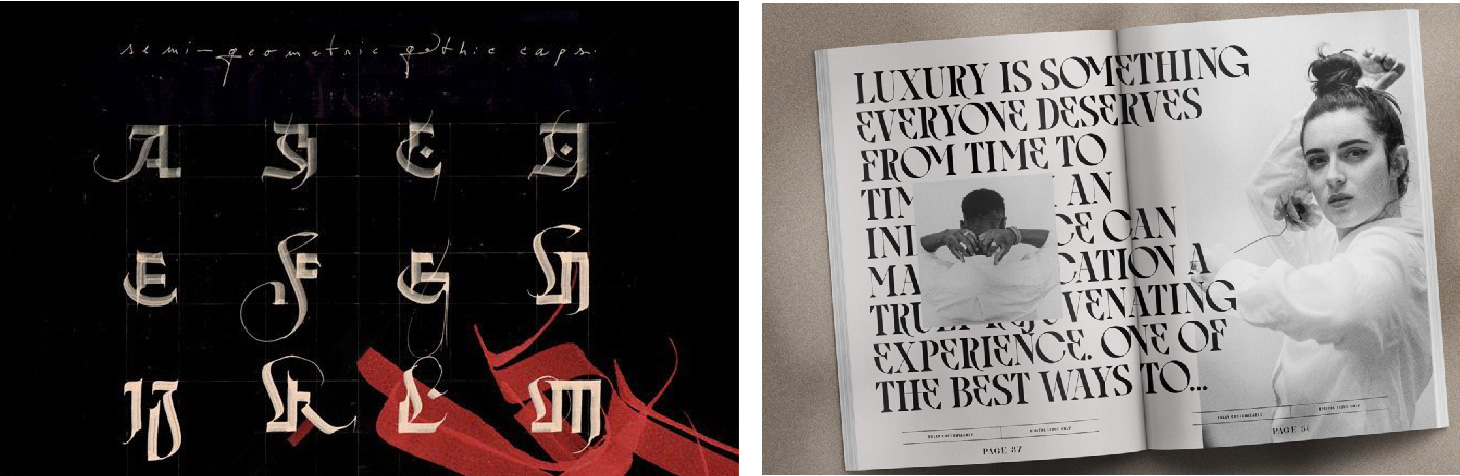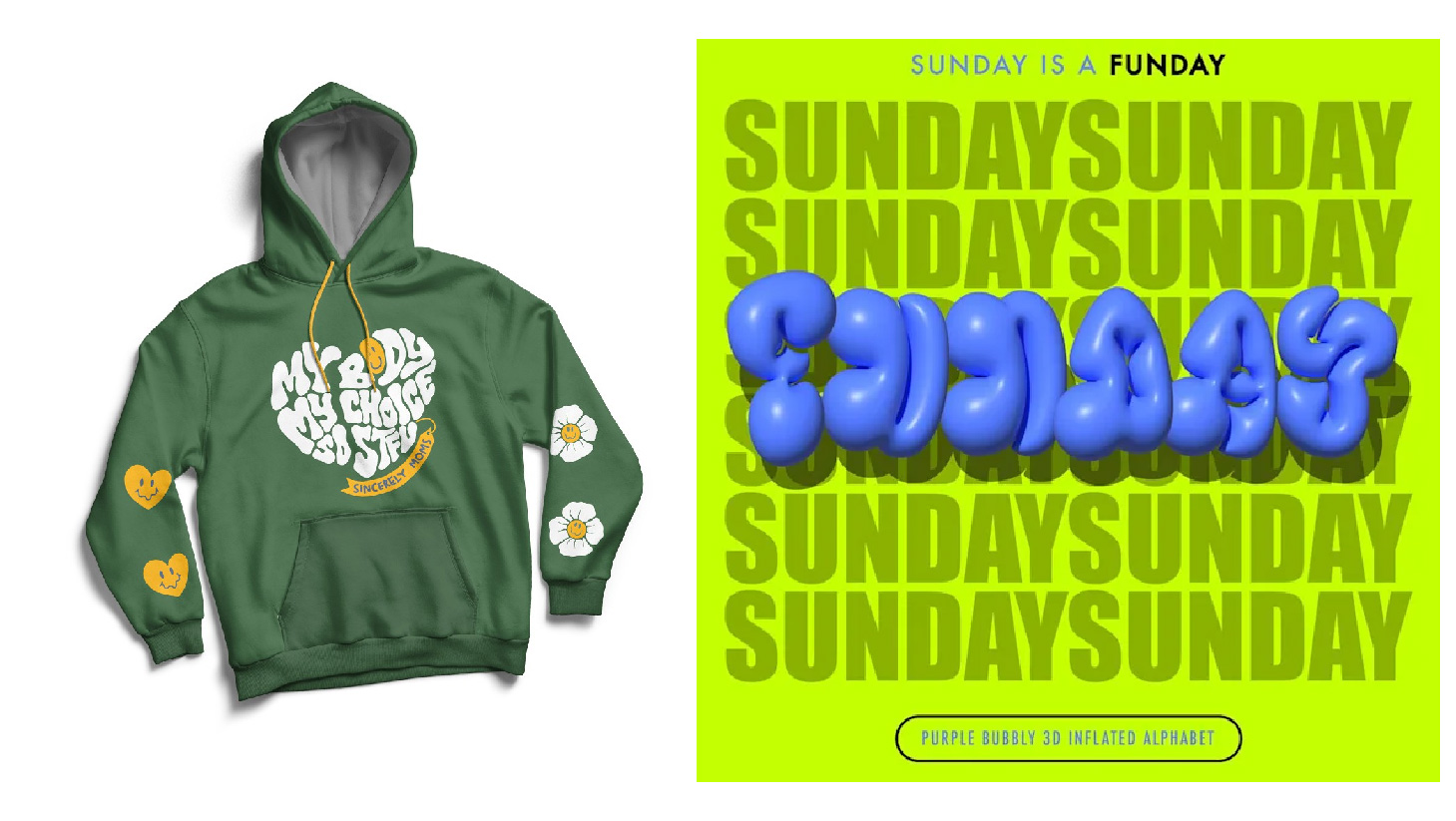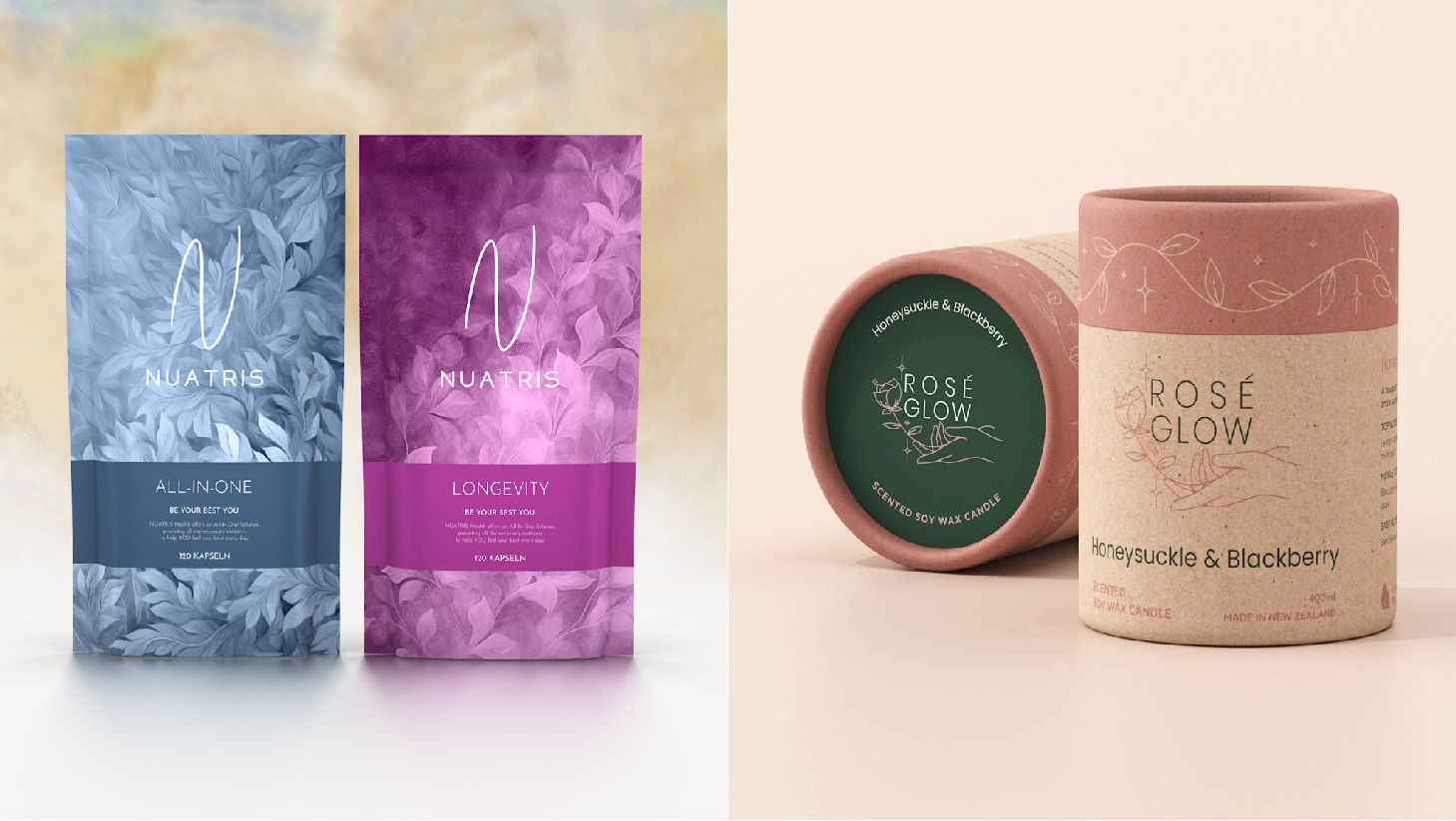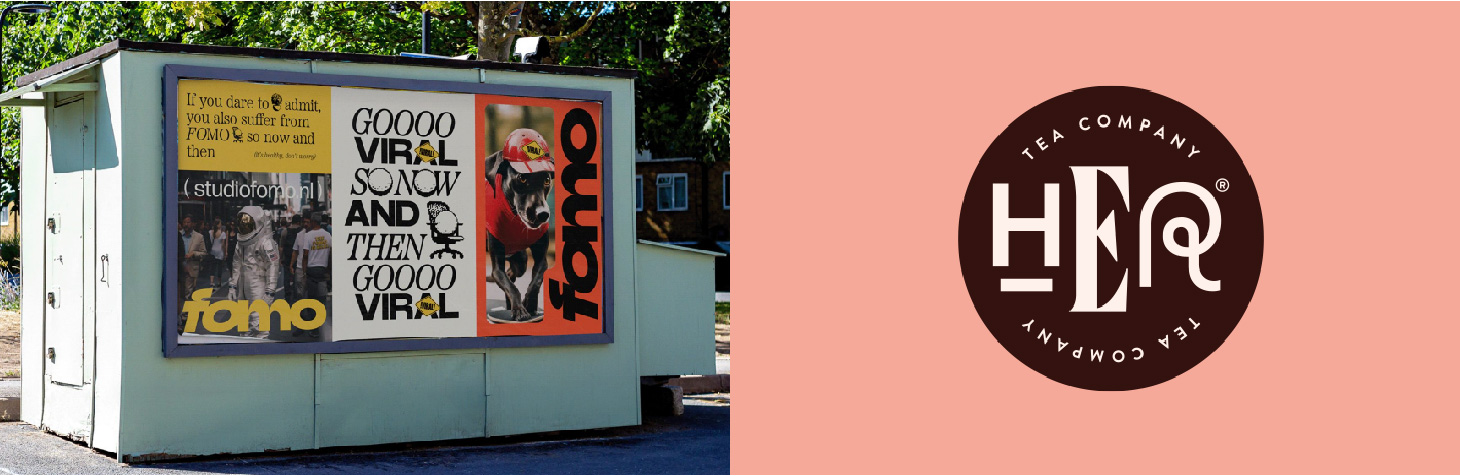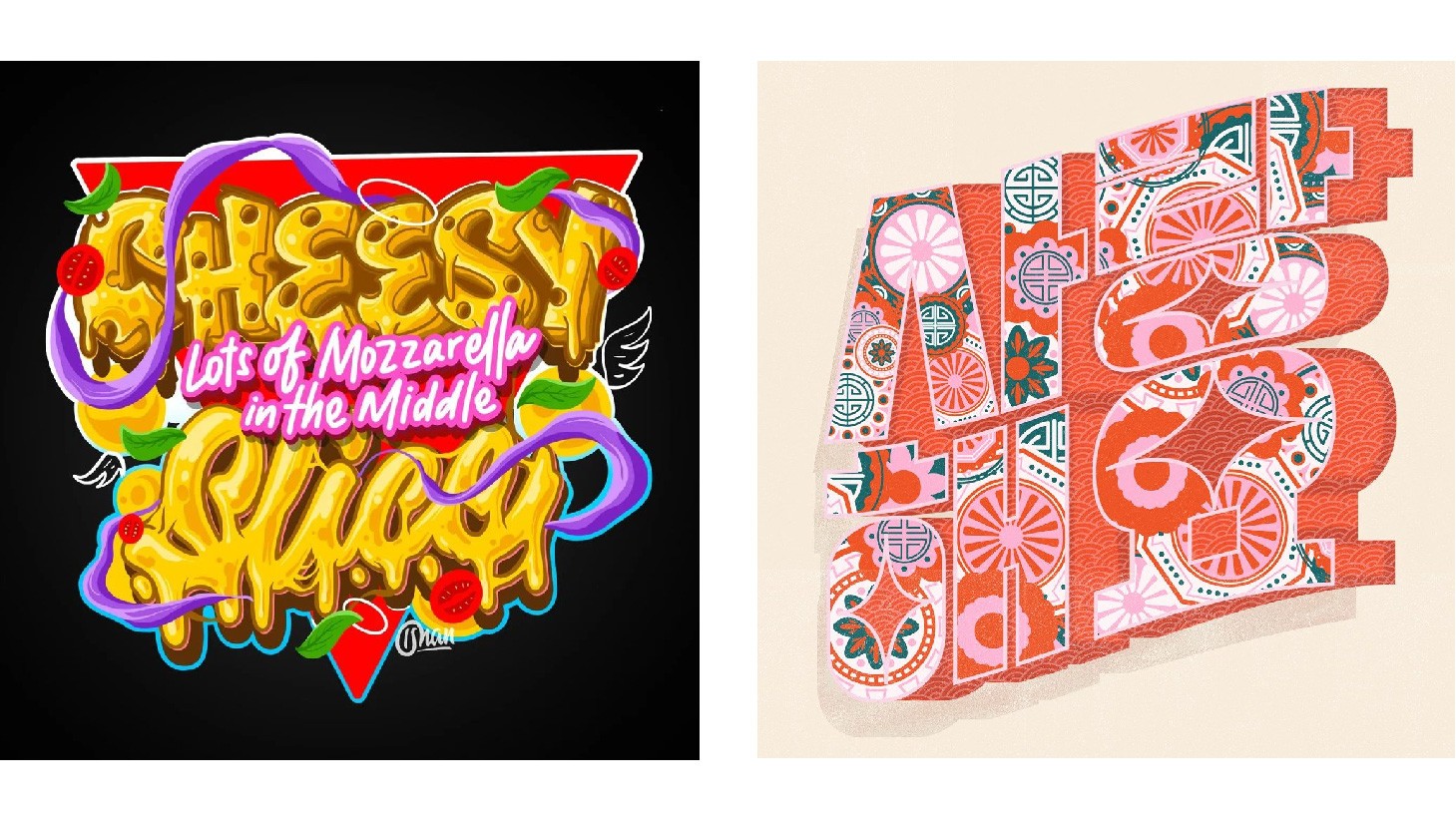
5 xu hướng thiết kế font chữ năm 2026 mà bạn không thể bỏ qua
Cùng Bee Art khám phá 5 xu hướng thiết kế font chữ 2026 được dự đoán sẽ làm mưa làm gió nhé!
Sự thay đổi của font chữ trong năm 2026
Nghệ thuật thiết kế đồ họa đang thay đổi với tốc độ chóng mặt. Mỗi năm, những công cụ mới và xu hướng thẩm mỹ mới lại định hình cách chúng ta đọc và cảm nhận thiết kế. Và 2026 là một năm đầy hứa hẹn với nhiều chuyển biến đột phá. Font chữ giờ đang trở thành “nhân vật” thật sự trong thế giới thiết kế: Yếu tố tạo nên cảm xúc, nhịp điệu và cá tính cho thiết kế. Từ typography chuyển động, 3D, đến màu sắc sinh động và kiểu chữ thủ công, năm nay là thời điểm mà font chữ trở nên sống động, linh hoạt và đầy sức biểu cảm.
Sự trở lại của font chữ hoài cổ - Retro
Năm 2026 là thời điểm cảm hứng hoài niệm gặp gỡ nét cá tính hiện đại. Các font chữ mang phong cách retro đang trở lại mạnh mẽ: Từ slab serif đậm nét, đường cong phóng khoáng của thập niên 70, đến chữ viết tay cổ điển vui tươi nhưng được làm mới trong bố cục mới đầy phá cách. Khi được kết hợp với chất liệu thô, bề mặt sần hay đường nét chữ phóng khoáng, không đều đặn, phong cách này mang lại cảm giác tự nhiên, chân thật và tràn đầy sức sống.
Xu hướng Font chữ cách điệu hoài cổ đang trở lại
Những font chữ retro đặc biệt phù hợp với thiết kế thương hiệu, poster hoặc ấn phẩm biên tập, nơi cá tính thị giác được đặt ngang hàng với khả năng đọc dễ dàng.
Font chữ thủ công, chữ viết tay (Handcrafted Fonts)
Giữa thời đại mà mọi chi tiết đều được căn chỉnh hoàn hảo đến từng pixel và AI có thể tạo ra font chữ chỉ trong chớp mắt, những nét chữ mang dấu ấn lại trở nên thật đặc biệt.
Font chữ viết thủ công thường có đường nét không đều, nét cọ phóng khoáng, bề mặt gồ ghề hay chút lem mực tự nhiên – chính những “khuyết điểm” ấy lại làm nên cá tính và cảm xúc riêng. Chúng mang lại sự ấm áp, gần gũi và chân thật, khiến người xem có cảm giác như đang chạm vào nét chữ thật được vẽ bằng tay.
Ngày nay, bạn có thể bắt gặp font chữ thủ công trong thiết kế thương hiệu, bao bì sản phẩm, bìa sách hay ứng dụng di động - ở bất cứ đâu mà thương hiệu muốn gần gũi, thân thiện.
Font chữ viết tay thủ công sẽ làm mưa làm gió năm 2026
Giữa thế giới của những thiết kế “chuẩn chỉnh” và máy móc hóa, font chữ thủ công xuất hiện như một lời nhắc nhẹ nhàng: đôi khi, chút mộc mạc và cảm xúc thật mới là điều khiến thiết kế trở nên đáng nhớ. Bạn sẽ thấy phong cách này xuất hiện ngày càng nhiều trong thiết kế thương hiệu, bao bì sản phẩm, thậm chí là ứng dụng di động: ở bất cứ đâu mà thương hiệu muốn trở nên thân thiện và mang hơi thở "con người".
Xu hướng thiết kế sử dụng font chữ không chân tinh tế
Khi nghĩ đến phông chữ tinh tế, chúng ta thường hình dung chữ viết tay mềm mại, lặp đi lặp lại, thường thấy trên thiệp mời đám cưới. Tuy nhiên, font chữ sans serif, với kiểu dáng đơn giản và thiết thực, không cần đến những chi tiết trang trí. Nhưng vào năm 2026, xu hướng thiết kế sử dụng font chữ sans serif sẽ bắt đầu bộc lộ sự tinh tế qua các nét vẽ thanh mảnh và khoảng cách chữ rộng rãi.
Font chữ không chân tinh tế, tối giản và linh hoạt sử dụng (Sưu tầm)
Hòa cùng xu hướng tối giản gần đây, xu hướng thiết kế font chữ sans serif tinh tế mang đến những phông chữ linh hoạt với hình thức giản dị, không làm lộn xộn bố cục, dù bạn có cố ý. Thông qua sự tinh tế font chữ này thể hiện sự tự tin và toát lên vẻ sang trọng và thanh lịch. Chúng đặc biệt được ưa chuộng trong các thiết kế bao bì ngành chăm sóc sức khỏe và thiết kế logo dạng chữ lồng, những dự án muốn tạo ra không gian thư giãn, chuyên nghiệp và hiện đại.
Xu hướng thiết kế sử dụng font chữ trừu tượng
Dù có phá cách đến đâu, hầu hết các font chữ vẫn giữ được sự đồng nhất khi các ký tự được hiển thị theo cùng một phong cách. Tuy nhiên, vào năm 2026, một xu hướng thiết kế font chữ mới thực sự phá vỡ chuẩn mực này. Các nhà thiết kế đã bắt đầu thử nghiệm với việc biến dạng các chữ cái, mang đến những yếu tố trừu tượng đột ngột trong từng từ hoặc đoạn văn.
Font chữ trừu tượng giúp thiết kế trở nên cuốn hút, sáng tạo (Sưu tầm)
Bạn có thể nghĩ rằng những hình thức trừu tượng của chữ cái sẽ khó đọc, nhưng tâm trí chúng ta có khả năng tự lấp đầy những khoảng trống, ngay cả khi một chữ cái hoàn toàn biến mất. Chính vì vậy, xu hướng thiết kế font chữ này không chỉ dừng lại ở việc in đậm những ký tự đơn giản mà còn nhấn mạnh vào tính nghệ thuật. Các nhà thiết kế có thể thay đổi kiểu dáng font, điều chỉnh tỷ lệ, thay đổi căn chỉnh, hoặc thêm những hình minh họa đồ họa vào giữa từ, tạo nên sự sáng tạo độc đáo và cuốn hút.
Khi áp dụng tính trừu tượng cho toàn bộ các chữ cái, các nhà thiết kế có nhiều phương tiện sáng tạo để làm nổi bật các cụm từ chính trong văn bản. Sự trừu tượng tinh tế không chỉ khuyến khích người đọc khám phá và tìm hiểu kỹ lưỡng, mà còn mang đến một phong cách cắt dán nghệ thuật vui tươi cho các dự án, nơi tính cá nhân và sáng tạo là điều quan trọng nhất.